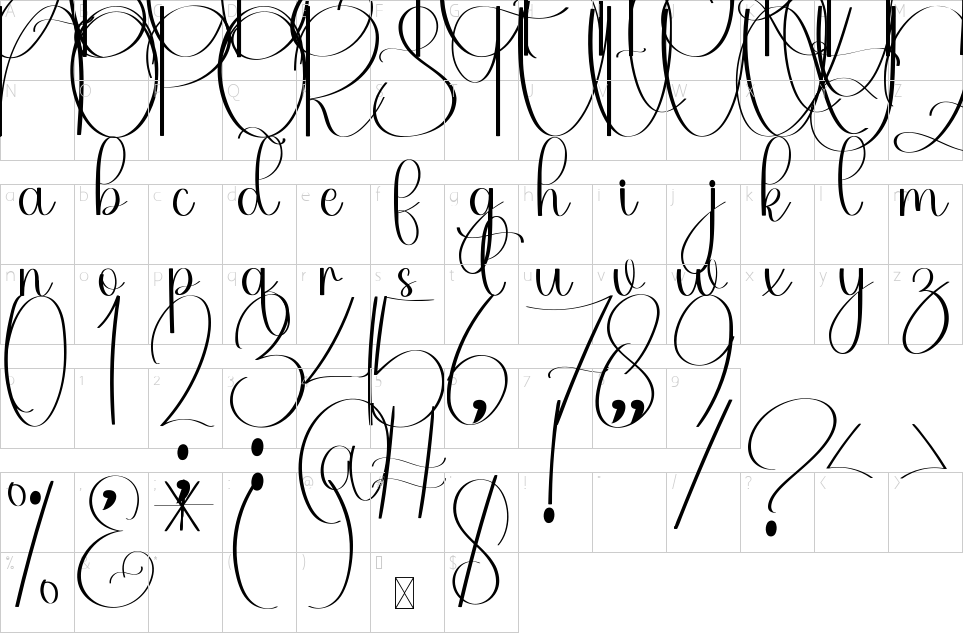
Always Font
Esta página de download apresenta a Always Font, uma elegante e versátil fonte que combina harmonicamente com diversas estilos de design. Desenvolvida pelo designer não informado na InermediaSTUDIO, essa fonte tem sido amplamente utilizada por criadores de conteúdo, designers gráficos e profissionais de web para adicionar um toque de sofisticação a seus projetos. Seu estilo clean e fácil de ler é perfeito tanto para criações digitais quanto para impressões físicas. Com uma facilidade de uso sem igual e uma aparência que se adapta bem à maioria das aplicações gráficas, Always Font torna-se um verdadeiro aliado dos profissionais. Baixe sempre essa fonte grátis agora e descubra por si mesmo como ela pode adicionar valor a seus projetos.
Mapa de caracteres da fonte Always Font